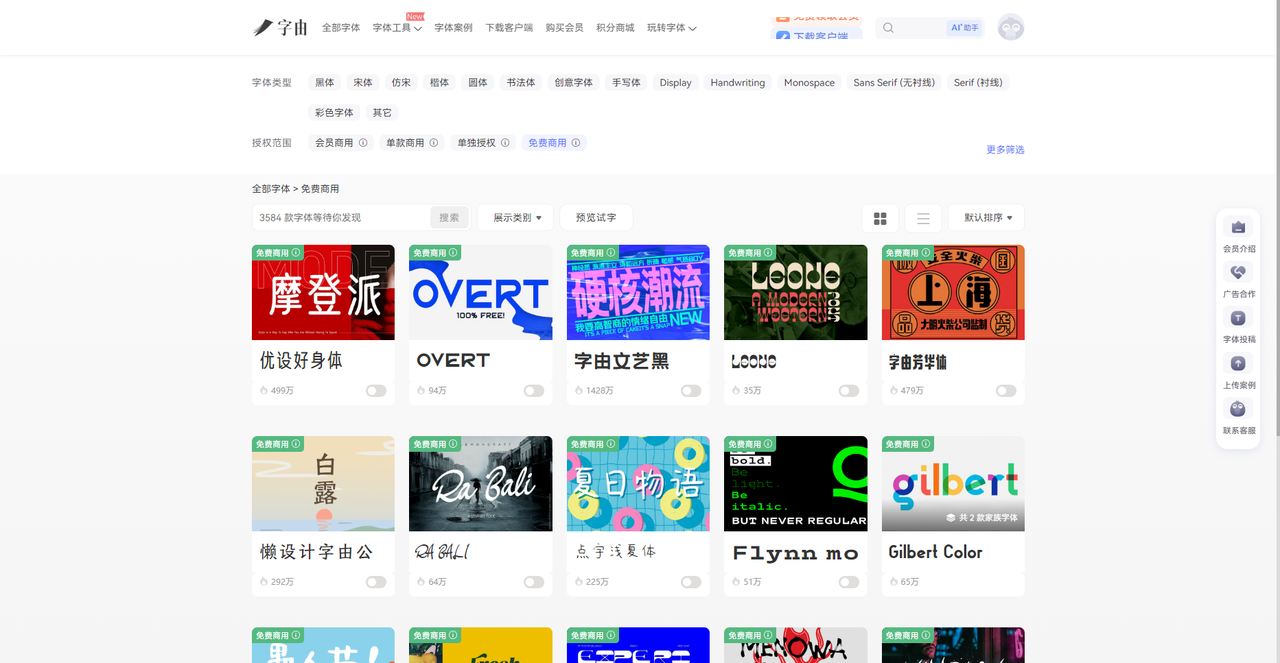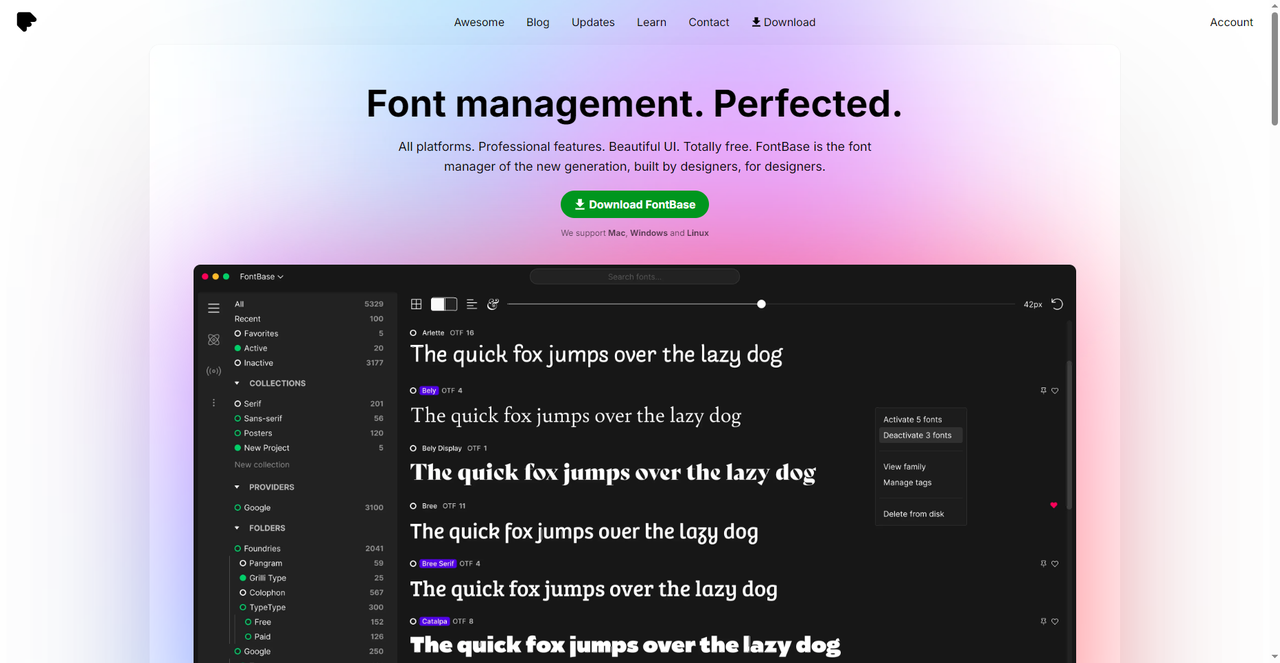
免费字体库下载哪里找?这一篇帮你收齐了
做设计这么长时间,我发现在找字体这件事上,遇到的问题基本上可以分为两种:第一种是电脑里存了好几 G 的字体包,但是真要用的时候还要费劲去翻找;第二种是每次做项目临时搜,如果能搜到好用的只能算自己运气好了。其实这两种方法都不算省心。说白了, 缺的是一个靠谱的免费字体库下载渠道——不用你自己到处收集,不用挨个查版权,打开就能用,用起来还顺手。今天我就把我最常用的 5 个免费字体库下载网站整理出来,方便大家使用!
第一个要推荐的免费字体库下载平台是字由。它隶属于上海驿创信息技术有限公司,自品牌创立以来,一直致力于解决设计师群体的用字问题。2017年,字由客户端正式发布,被粉丝们热情地称为“字体应用管理神器”。同年3月,字由官网上线,从此打通了从官网到客户端的贯通应用和服务。
字由不仅给客户提供字体,还分享技巧教程、设计趋势、素材合集等,同时以平台化的运营聚合了大量设计相关群体,组织和参与各类活动。目前,字由聚集了超千万设计师、创意人才、运营管理人员、商务人士、在校学生等对字体应用管理有苛求的忠实粉丝。
核心功能,字体一键应用
字由最实用的功能是在PS、AI、Figma、Sketch、CDR等软件里一键切换字体。在软件里选中文字图层,回到字由客户端点击想要的字体,文字实时切换,不需要下载、安装、重启。试一款字体只要1秒钟,这才是免费字体库下载该有的样子。
庞大字体库,3584款免费商用随便挑
进入主页以后点击“全部字体”,左侧有详细的筛选栏,你可以按类型,也可以按热度和授权范围来,完全不用担心版权的问题。
字体推荐,总有你想要的那一款
- 字由文艺黑:既有黑体的稳重,又带手写感,适合标题、海报
- 优设标题黑:方正有力,适合电商设计、活动海报
- 江西拙楷:手写楷书风格,适合国风、文创设计
- 字由芳华体:手写风格,笔画柔和,适合文艺类设计
个人云字库,无须担心数据丢失
而且字由还支持上传本地字体到云端,换设备登录直接激活使用。电脑坏了也不用担心字体丢失,只要账号在,字体就在。
2、FontBase
FontBase 是一款专业的字体管理软件,支持 Mac、Windows 和 Linux 三个平台,而且完全免费。它的定位是“由设计师为设计师打造的新一代字体管理器”。如果你的设计软件当中不仅限于 PS ,那么这个网站将是十分合适的。最主要的是支持多平台,因为有的设计师使用的设备是 Mac ,要是有的软件或者是字体不兼容也是个麻烦事。从图中我们也不难看出,FontBase 的界面非常简洁现代,主打“字体管理 perfected”。它可以帮助你快速激活/停用字体,分类管理,实时预览,而且不会拖慢系统速度。
3、Typewolf
Typewolf 是一个专注于字体趋势和推荐的网站,由设计师 Jeremiah Shoaf 运营。首页展示的是它整理的“The 40 Best Free Fonts Available on Google Fonts”(Google Fonts上40款最佳免费字体),而且这40款字体都是开源免费的,并且来自知名的字体设计师和代工厂。虽然整体上的字体数量比不上一般的网站,但是绝对精品,有一些字体可以拿来反复使用,最主要的是网站还提供40款字体的ZIP打包下载,订阅邮件即可免费获取。如果你不知道 Google Fonts 里哪些字体好用,来这个网站就对了。
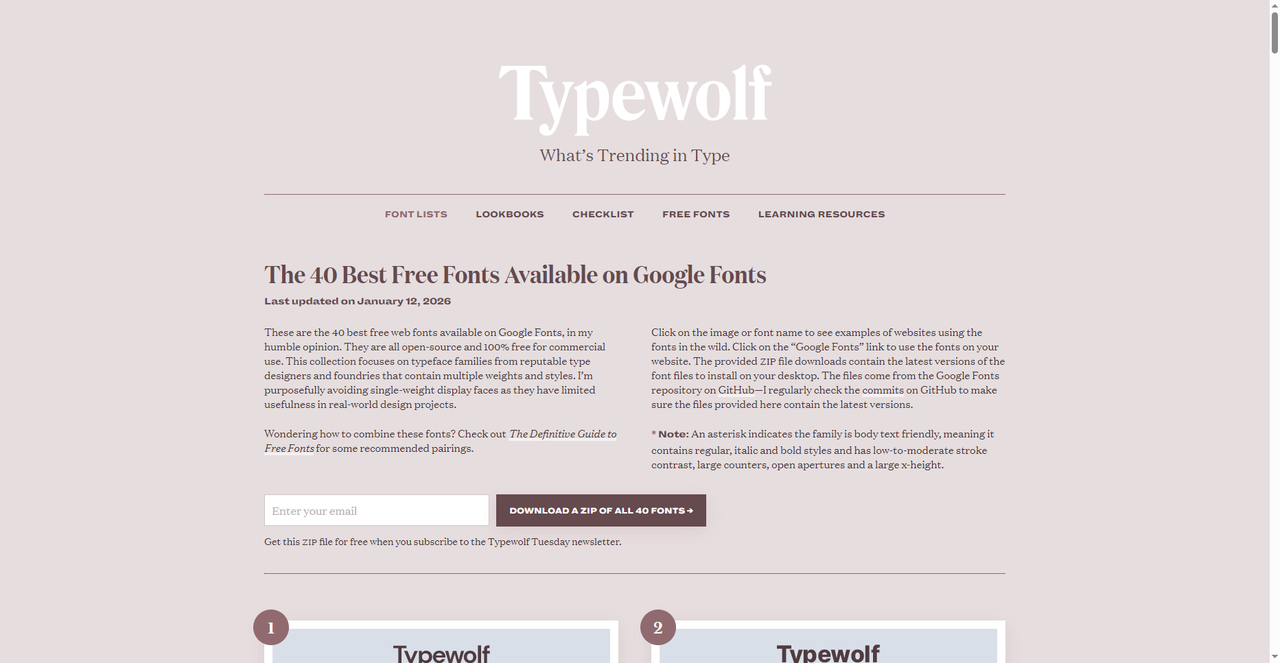
4、Befonts
Befonts 是一个提供免费字体下载的设计资源站,同时也有付费的 Premium 字体板块。而且它的免费办款不是一成不变的,每过一段时间点进去你都会发现有新的免费优质字体可供下载,我是经常会来这个网站逛逛,发现好的新更新的免费字体会直接下载下来,有种薅羊毛的感觉。近期更新的免费字体我推荐的有:
- QEPHODERN:现代极简科技感显示字体
- Bonats Restorly:复古风格字体
- VELORA BLOOM:独特的显示字体双胞胎(无衬线+衬线)
- Palma Club:粗体手写字体
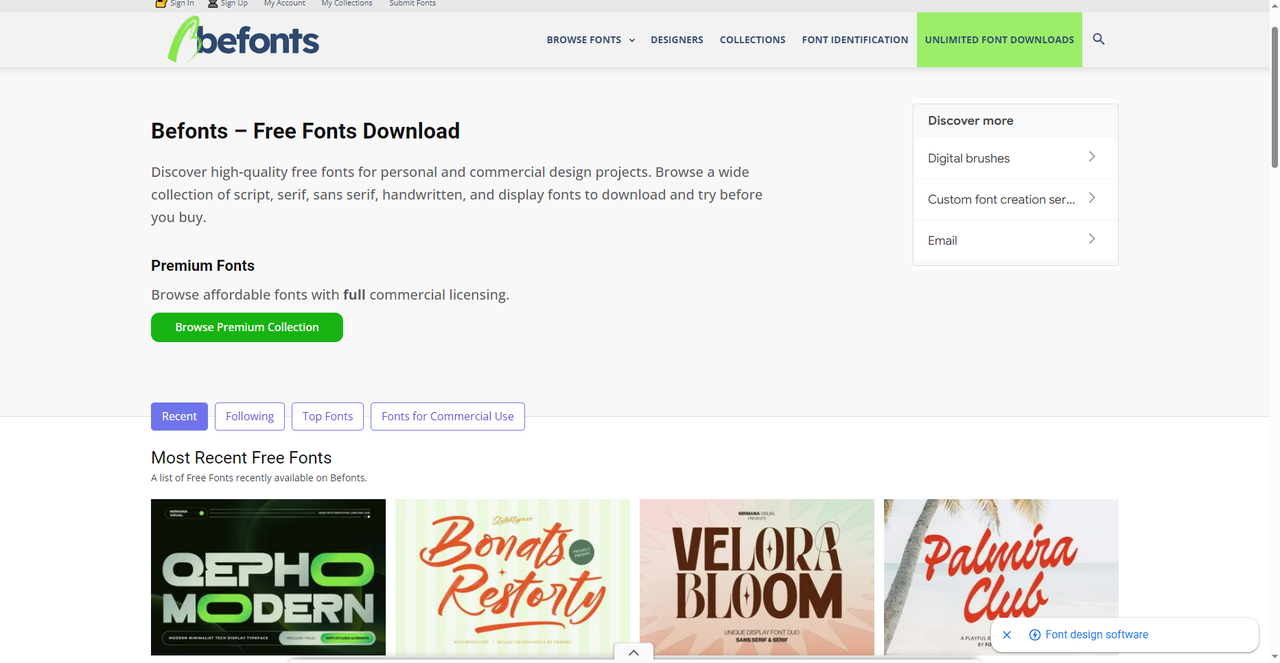
5、FREE FONTS(All Free Fonts)
FREE FONTS 目前收录了 8400 款免费可下载字体,数量巨大,虽然页面没有是说很精致,但是字体数量这方面绝对管够,不论你要是什么风格几乎在这里都可以找到。首页上会展示最新上传和热门的字体,每一款都配有高清预览图和风格标签。同样的,在使用和下载之前记得看一下授权标签!
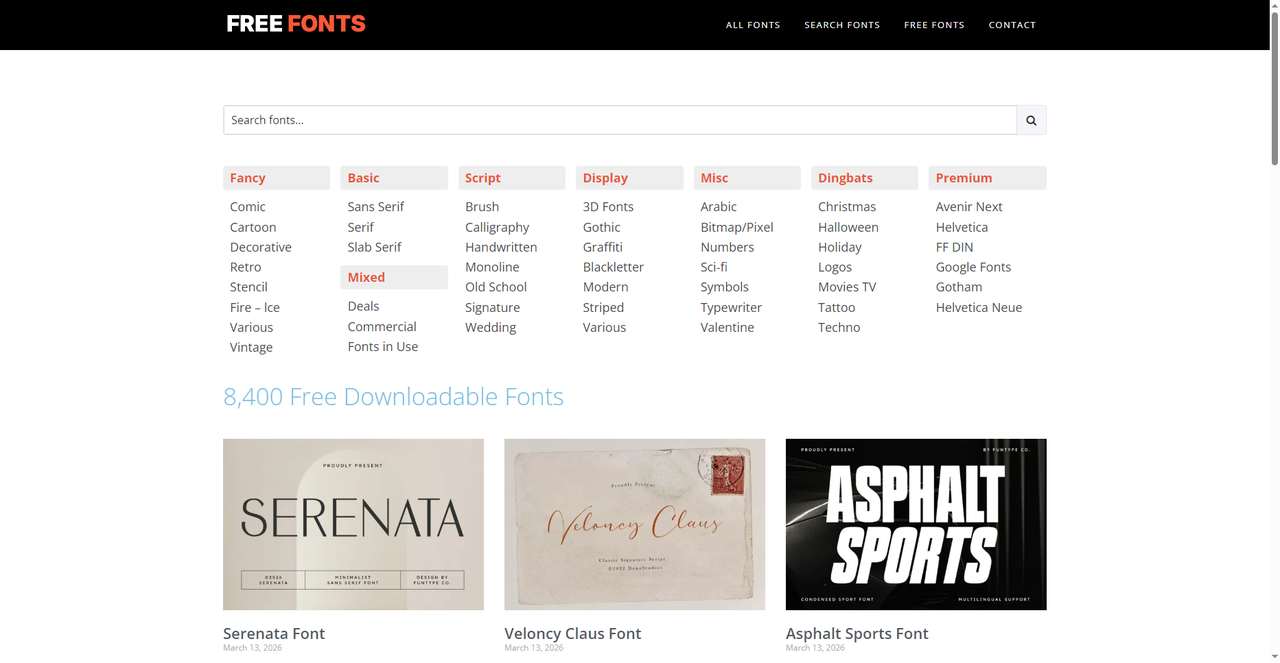
针对我刚开始说的问题,这几个网站结合起来以后基本上都能解决,比如说FontBase 适合管理本地字体,Typewolf 帮你从海量里挑精品,Befonts 适合常逛常新淘新鲜货,FREE FONTS 大体量字体风格多元化,总有你喜欢的。但是其实如果想一步到位的话我还是会推荐字由,它更像是把这几个网站的功能都集合到一起,你可以在字体首页慢慢逛,也可以通过个人云字库来管理你下载的字体,如果你也在找一个能长期使用的免费字体库下载网站,选字由就对了。